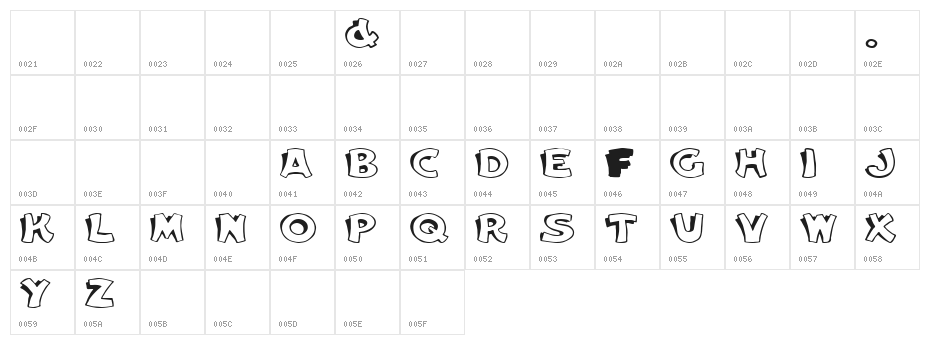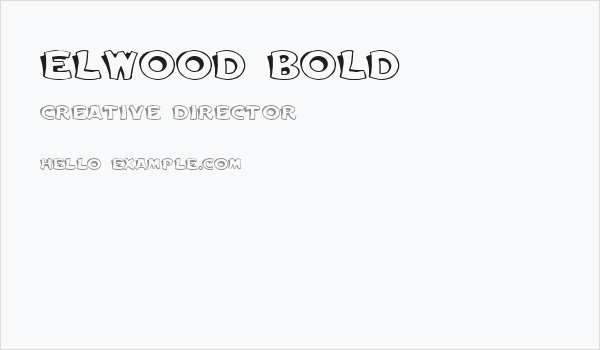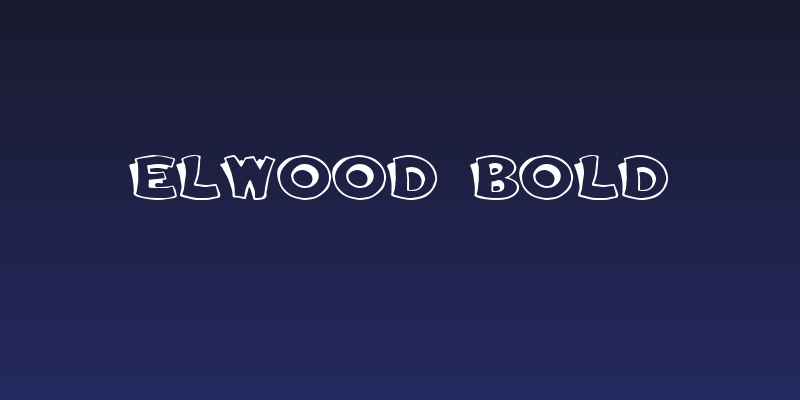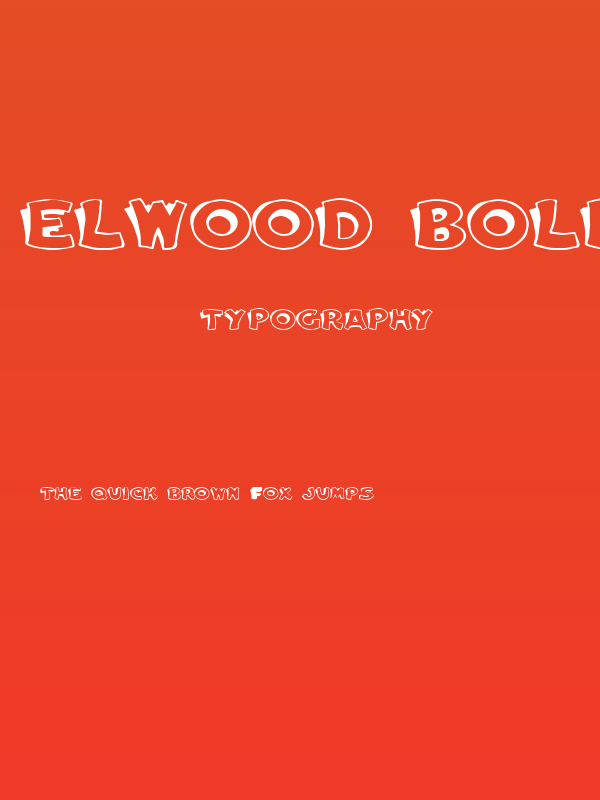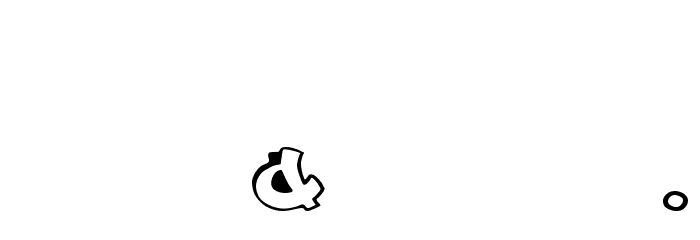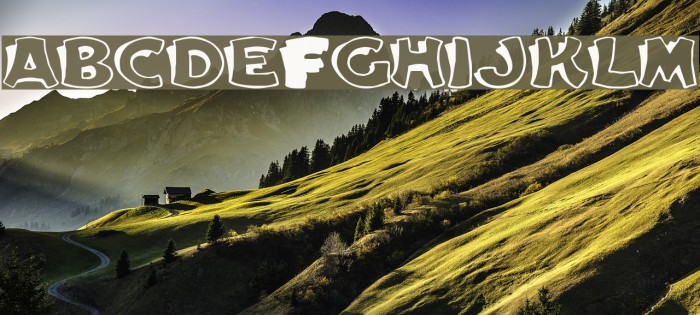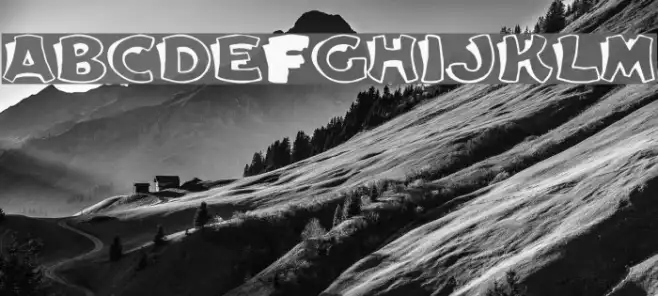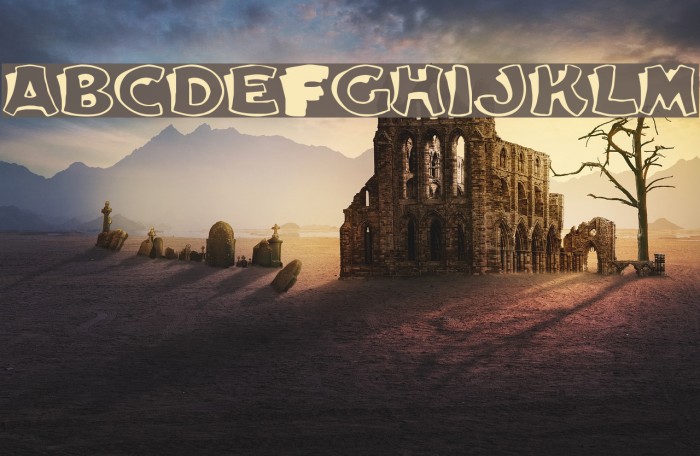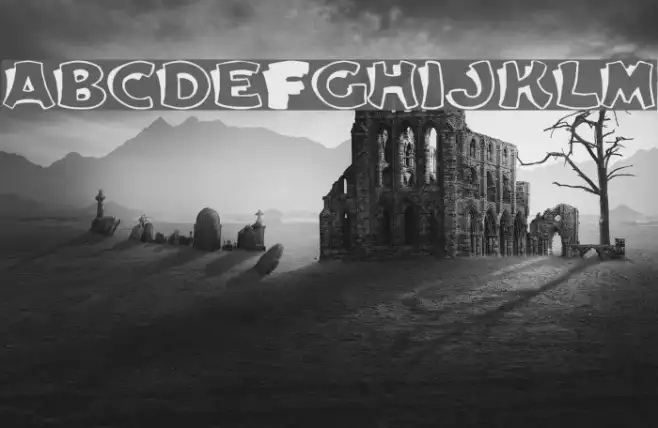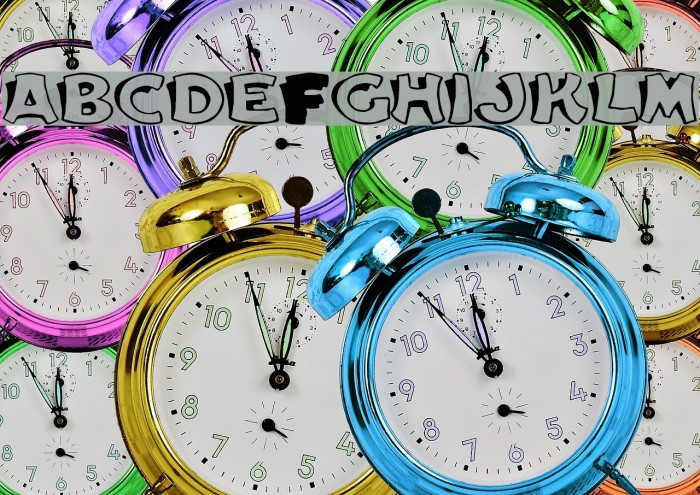
Elwood Bold Font
| Gesamtstil | Playful, Cartoonish |
| Vorgeschlagene Projekte | Ideal for children's books, comic strips, playful branding, and eye-catching posters. |